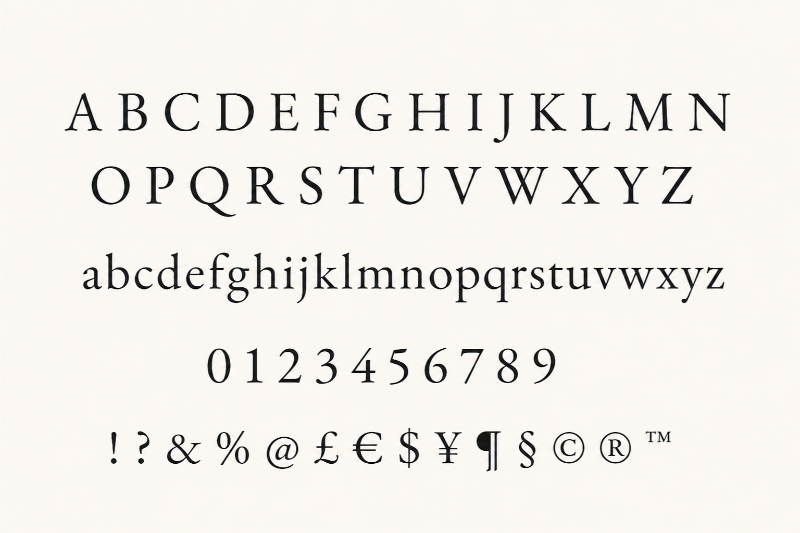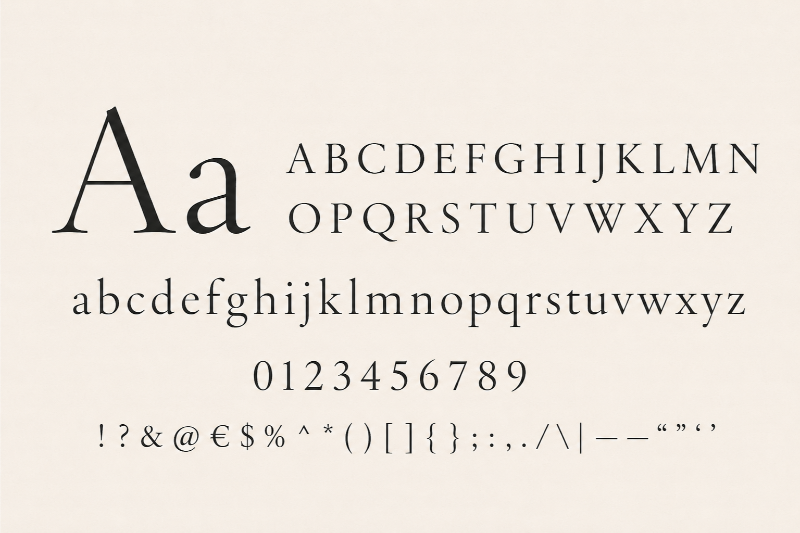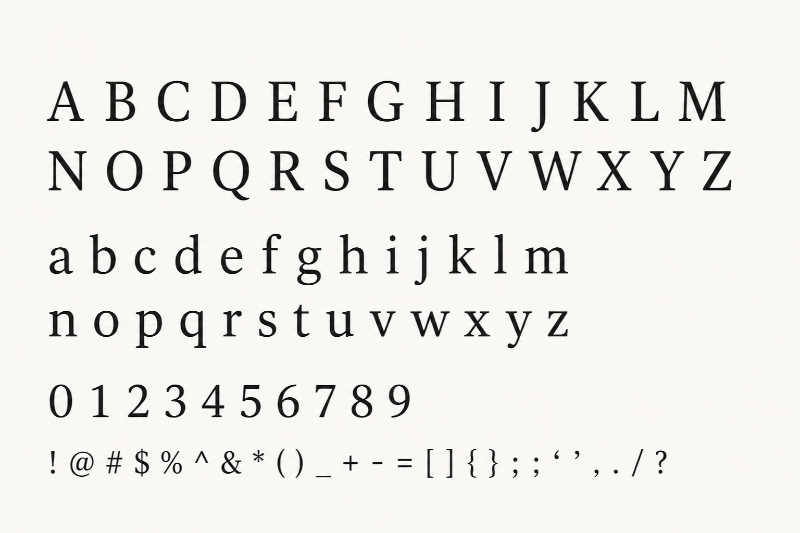
Trong lĩnh vực thiết kế, font chữ không chân thường gắn liền với vẻ đẹp tối giản, gọn gàng và hiện đại. Ngược lại, khi muốn tạo cảm giác sang trọng, tinh tế, cổ điển nhưng vẫn bền vững theo thời gian, font chữ có chân lại là lựa chọn gần như không thể thay thế.
Tuy nhiên, vấn đề khiến nhiều designer Việt đau đầu là không phải font Serif nào đẹp cũng hỗ trợ tiếng Việt tốt. Có những font nhìn rất cuốn trên Pinterest, Behance hay các bộ sưu tập thiết kế quốc tế, nhưng khi tải về sử dụng lại gặp lỗi dấu, lệch ký tự hoặc hiển thị tiếng Việt thiếu chuyên nghiệp. Vì vậy, trong bài viết này, In Đại Minh sẽ tổng hợp hơn 15 font chữ có chân Việt hóa đẹp, dễ ứng dụng và ổn định khi gõ tiếng Việt.
Font chữ có chân Serif là gì?
Font chữ có chân, hay còn gọi là Serif Font, là nhóm kiểu chữ có thêm những nét nhỏ ở phần đầu hoặc cuối các nét chính của ký tự. Những chi tiết này thường được gọi là “chân chữ”. Chúng không chỉ tạo cảm giác cổ điển, sang trọng mà còn giúp mắt người đọc di chuyển theo dòng chữ dễ hơn, đặc biệt khi dùng trong văn bản dài, sách, tạp chí hoặc các thiết kế cần sự trang trọng.
Để sử dụng font Serif đúng tinh thần thiết kế, bạn nên nắm được 4 nhóm Serif phổ biến sau:
Old Style – Nhóm cổ điển
Đây là nhóm Serif ra đời từ khoảng thế kỷ 15, mang đậm tinh thần truyền thống và gần gũi. Đặc điểm dễ nhận biết là sự chênh lệch giữa nét thanh và nét đậm không quá lớn, đường nét mềm mại, dễ đọc và tạo cảm giác ấm áp. Một ví dụ tiêu biểu của nhóm này là Garamond.
Transitional – Nhóm chuyển tiếp
Transitional Serif là bước trung gian giữa phong cách cổ điển và hiện đại. Nhóm này có độ tương phản nét thanh – nét đậm rõ hơn Old Style, bố cục chữ cân đối và sắc nét hơn. Vì vậy, nó thường mang lại cảm giác chỉn chu, nghiêm túc và dễ ứng dụng trong nhiều loại tài liệu. Ví dụ quen thuộc nhất là Times New Roman.
Modern / Didone – Nhóm hiện đại
Modern Serif, hay còn gọi là Didone, là đại diện rõ nhất cho vẻ đẹp sang trọng, thời thượng và cao cấp. Đặc trưng của nhóm này là độ tương phản rất mạnh: nét mảnh cực mảnh, nét đậm rất dày. Chính sự đối lập này tạo nên cảm giác tinh tế, đắt giá và thường xuất hiện trong thiết kế thời trang, mỹ phẩm, tạp chí cao cấp hoặc nhận diện thương hiệu luxury. Một số font tiêu biểu là Didot và Playfair Display.
Slab Serif – Nhóm chân vuông
Khác với hình dung quen thuộc rằng Serif luôn mềm mại và cổ điển, Slab Serif mang đến cảm giác mạnh mẽ, chắc chắn hơn rất nhiều. Phần chân chữ của nhóm này thường dày, vuông vức và có tính hình khối rõ ràng. Nhờ đó, Slab Serif rất phù hợp với các thiết kế cần sự nổi bật, khỏe khoắn, nam tính hoặc hiện đại. Ví dụ tiêu biểu là Roboto Slab.
Bộ sưu tập 15+ font chữ có chân Việt hóa đáng dùng nhất
Nhằm giúp bạn dễ dàng tìm được kiểu chữ phù hợp mà không mất quá nhiều thời gian giữa hàng trăm lựa chọn khác nhau, chúng tôi đã tổng hợp danh sách 15+ font chữ có chân Việt hóa đáng dùng dưới đây.
Playfair Display
Playfair Display được xem là một trong những font Serif nổi bật nhất khi dùng cho tiêu đề, bìa tạp chí hoặc các thiết kế mang hơi hướng thời trang. Điểm mạnh của font này nằm ở độ tương phản giữa nét thanh và nét đậm rất rõ, giúp chữ trở nên cuốn hút, sang trọng và nổi bật khi đặt ở kích thước lớn.
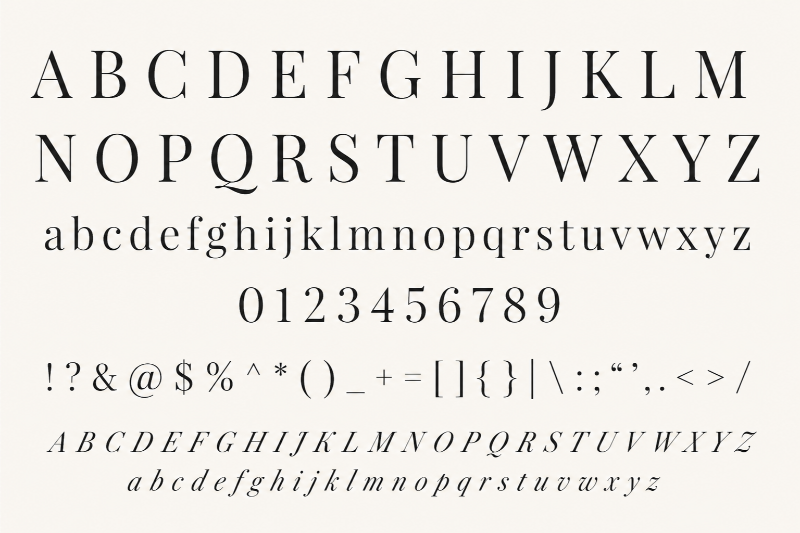
Cormorant Garamond
Cormorant Garamond mang vẻ đẹp mềm mại, bay bổng và có chút hoài niệm. Kiểu chữ này tạo cảm giác lãng mạn, tinh tế nên rất hợp với các thương hiệu spa, beauty salon, mỹ phẩm, thiệp cưới, thơ ca hoặc những thiết kế cần chất nghệ thuật nhẹ nhàng.
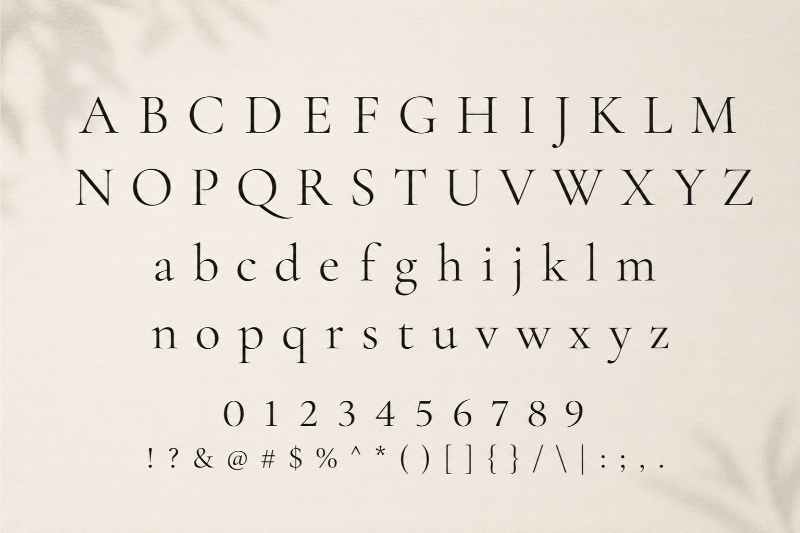
Didot Việt hóa
Didot là một biểu tượng kinh điển của phong cách xa xỉ và đẳng cấp. Với nét chữ thanh mảnh, sắc sảo cùng độ tương phản mạnh, Didot đặc biệt phù hợp để làm logo, tiêu đề thương hiệu thời trang, mỹ phẩm cao cấp hoặc các thiết kế luxury. Khi kết hợp với bố cục thoáng và nhiều khoảng trắng, font này tạo hiệu ứng thị giác rất “đắt tiền”.
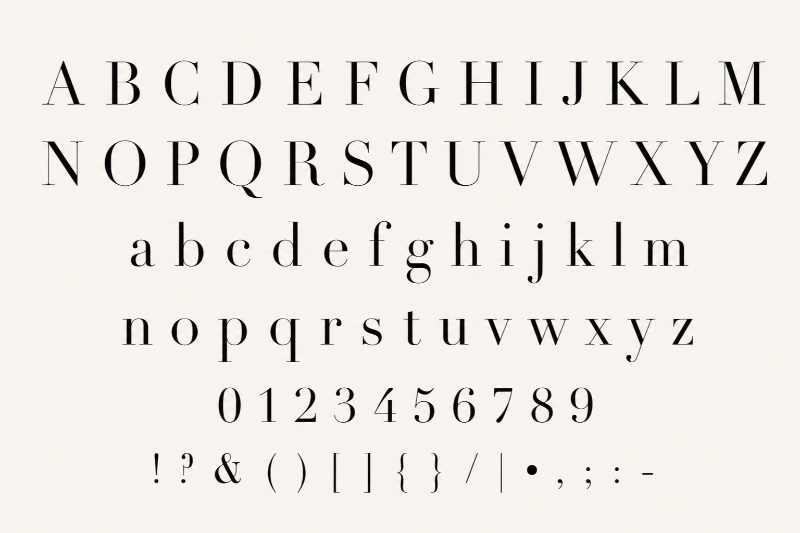
Prata
Prata gây ấn tượng bởi những đường cong mềm mại, tinh tế nhưng vẫn giữ được sự sắc nét cần thiết. Font này mang lại cảm giác thanh lịch, hiện đại và có chiều sâu, phù hợp cho tiêu đề website, nhận diện thương hiệu, poster hoặc các thiết kế cần sự chỉn chu nhưng không quá cứng nhắc.
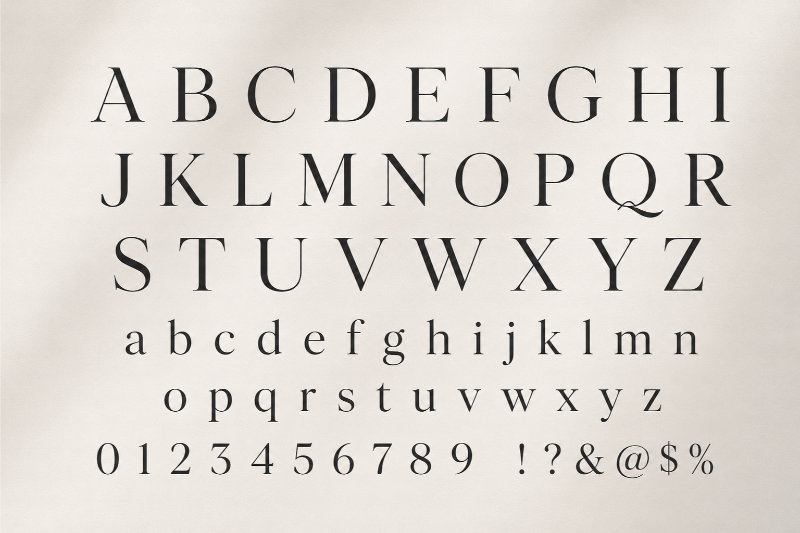
Vidaloka
Vidaloka có phần đuôi chữ uốn nhẹ, tạo cảm giác cổ điển và mang chút hơi thở vintage. Tuy nhiên, font này không bị cũ hay sến, mà vẫn giữ được sự duyên dáng và nổi bật. Vidaloka rất phù hợp cho các thiết kế về thời trang, quán cà phê, tiệm bánh, studio ảnh hoặc những thương hiệu muốn tạo dấu ấn mềm mại nhưng khác biệt.
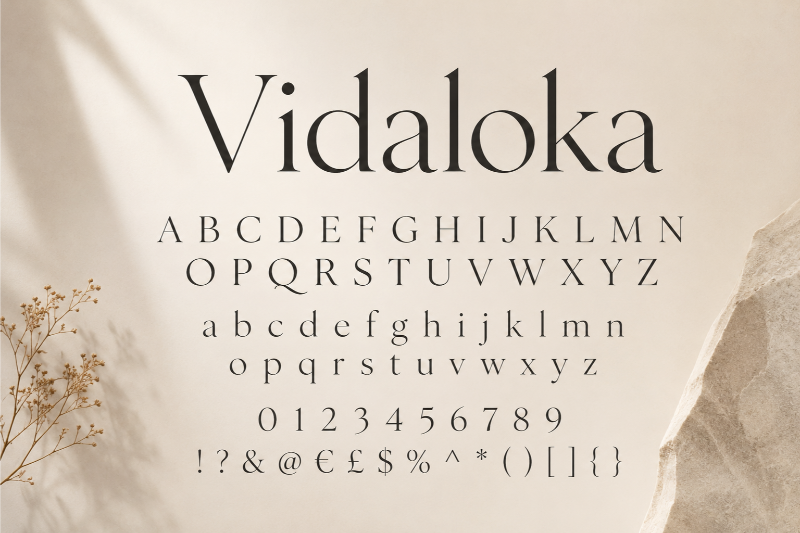
Lora
Lora là sự giao thoa tinh tế giữa cảm hứng thư pháp truyền thống và phong cách thiết kế kỹ thuật số hiện đại. Font chữ này có đường nét mềm mại, dễ đọc, phù hợp để sử dụng trong các đoạn văn bản dài, bài blog, tạp chí online hoặc nội dung cần cảm giác nhẹ nhàng mà vẫn chuyên nghiệp.
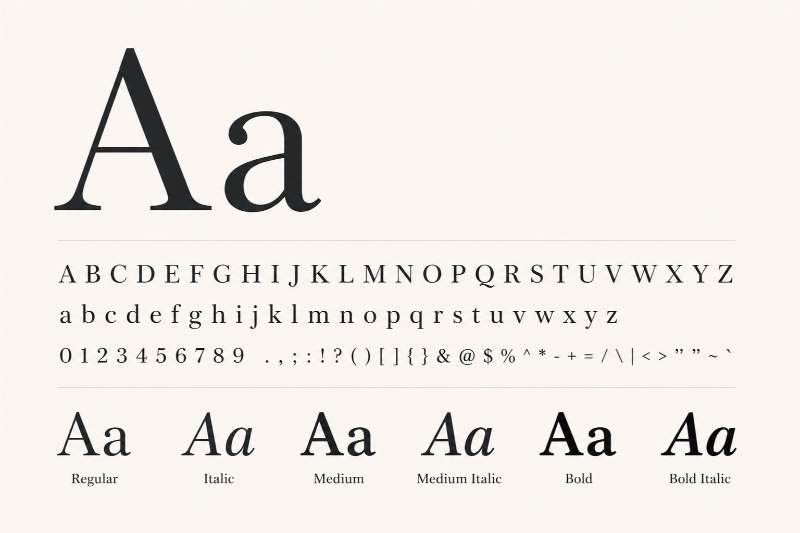
Merriweather
Merriweather được thiết kế tối ưu cho khả năng hiển thị trên màn hình. Dù người đọc xem nội dung trên máy tính, máy tính bảng hay điện thoại có kích thước nhỏ, font này vẫn giữ được độ rõ ràng và dễ đọc. Đây là lựa chọn rất đáng cân nhắc cho website, blog, landing page hoặc các bài viết dài.
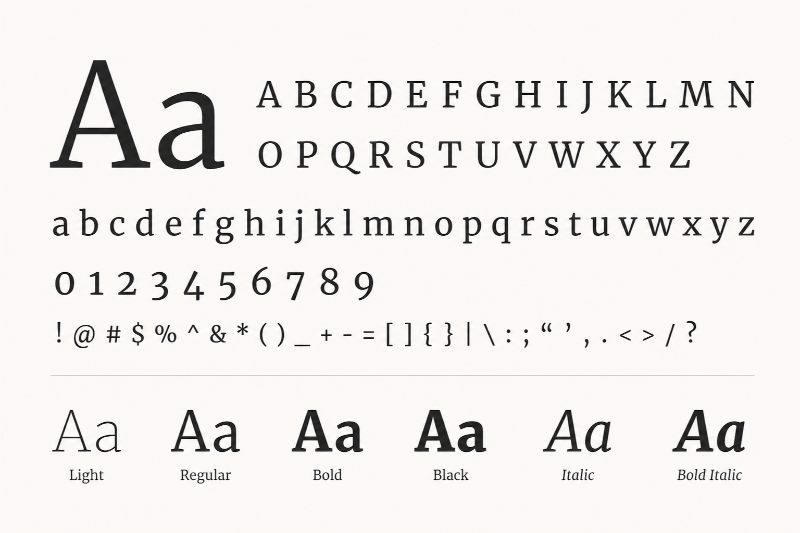
Trên đây là danh sách 15+ font chữ có chân Việt hóa đẹp, chuẩn cho Designer mà bạn có thể tham khảo để ứng dụng trong các dự án thiết kế. Một font chữ có chân được chọn đúng cách không chỉ giúp bố cục trở nên chuyên nghiệp hơn mà còn nâng tầm cảm xúc và giá trị thẩm mỹ cho toàn bộ sản phẩm.